文字化けして表示できない可能性のある文字「外字」
ここでいう外字は、PCでテキスト入力を行う際、変換しても表記できない標準的に備えられている以外の文字を意味し、人名や地名といった漢字の異体字や枠付き文字や単位記号、省略文字、シンボルマークなどの特殊な記号や絵文字など、文字コードに登録されていない文字を利用者やメーカーが独自に字形を定義した文字。
有名な外字として𠮷野家の「𠮷」や髙島屋の「髙」などがある。
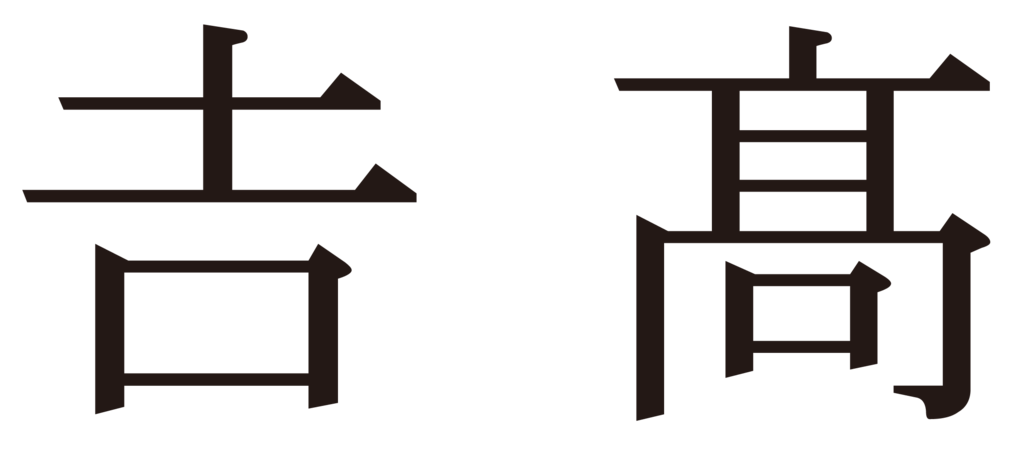
𠮷野家の吉は、士ではなく土。
髙島屋の髙は、高ではなく、はしご高。
文字化けなどの問題を引き起こす「環境依存文字」
電子的に扱う文字データの中でソフトウェアやハードウェアによって違う文字に表示されたり、全く表示印刷できなかったりするものの慣用的な総称。または機種依存文字ともいう。
異体字
異体字は、旧字な標準の字体とは異なるが、発音や意味などが一緒の字体。OpenTypeフォントでは1つの文字に対して「会」や「會」など異体字が定義されていることがある。
旧字体
漢字の字体で「当用漢字字体表」で新たに定められた字体に対していわれる古くから使用されていた文字
人名外字の例
記号外字の例
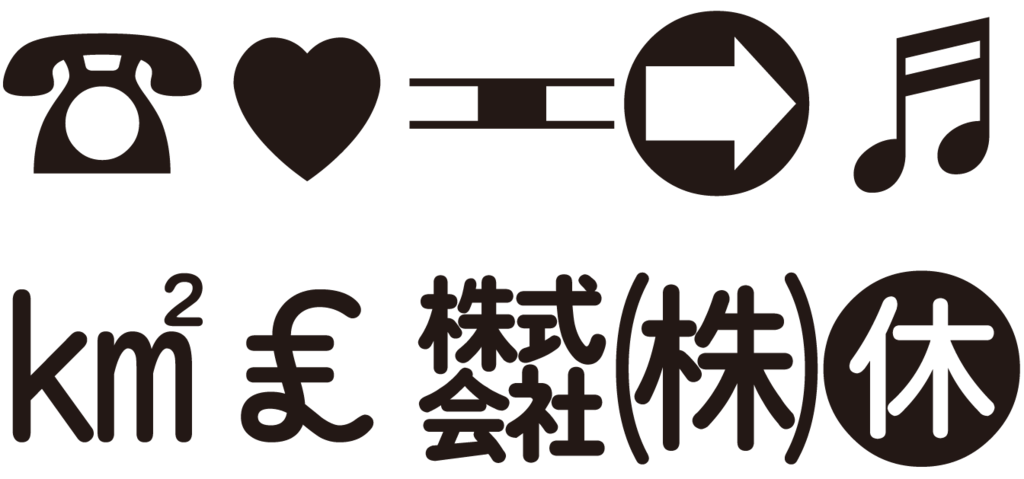
文字化け
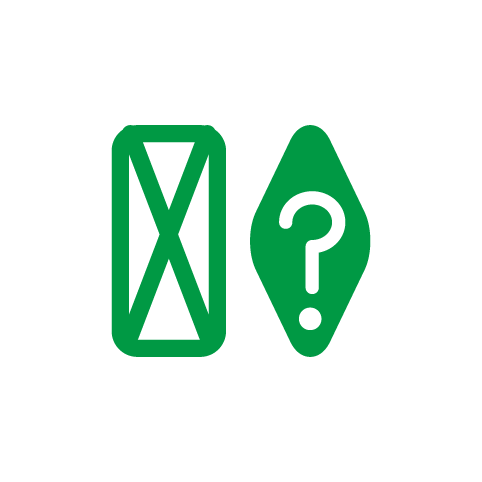
「文字化け」とは、入力したテキストが正しく表示されず、上記のように化けてしまう現象で、外字と言われるテキストを入力すると変換の際に上記のような現象を起こしてしまったりする。
文字化けが起こる主な要因は、コンピュータで文字を表示する際に、正しく表示されない現象のこと。主な原因は、ソフトウェアやハードウェアの不具合、文字コードの違い、エンコーディングとデコーディングの不一致、文字フォントの違いなどが原因となる。
外字問題を解決できる外字対応書体パッケージ情報
PC上で変換できない文字を表示できるようにするため、世の中には人名記号外字を集めた外字対応書体を集めた「人名記号外字3」や外字を作成するツール「Gaiji Builder2」といったソフトなどが存在する。